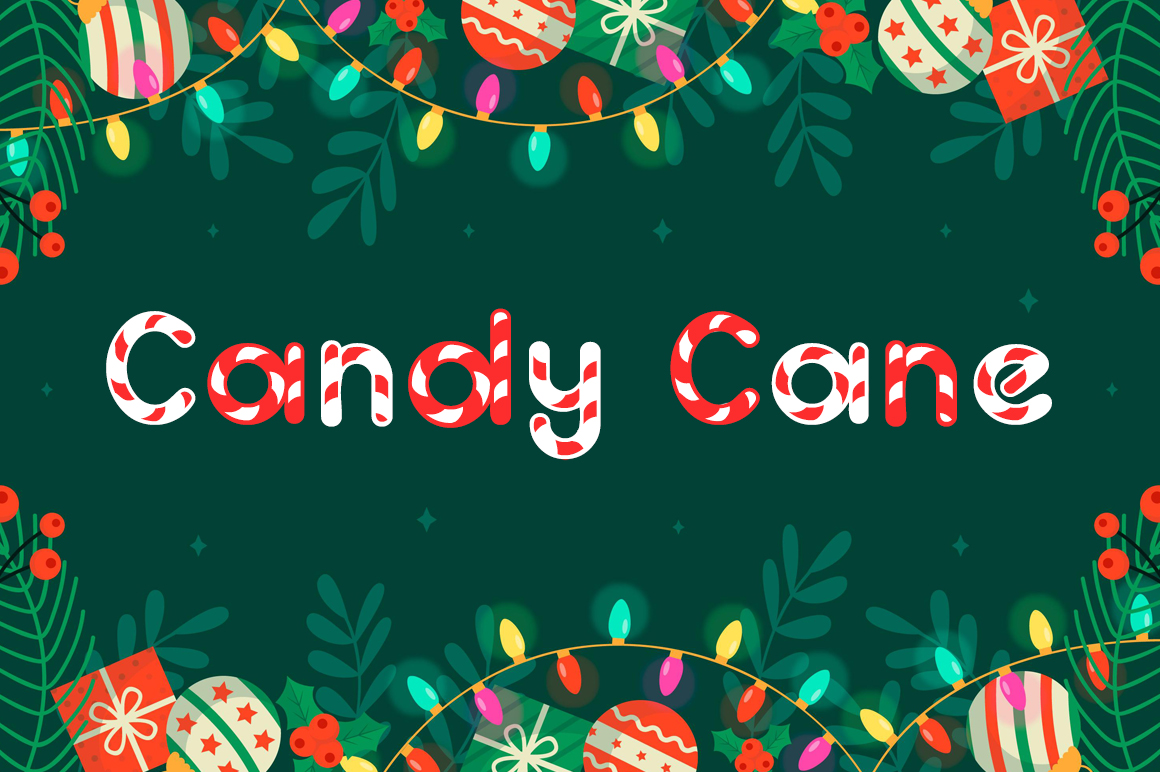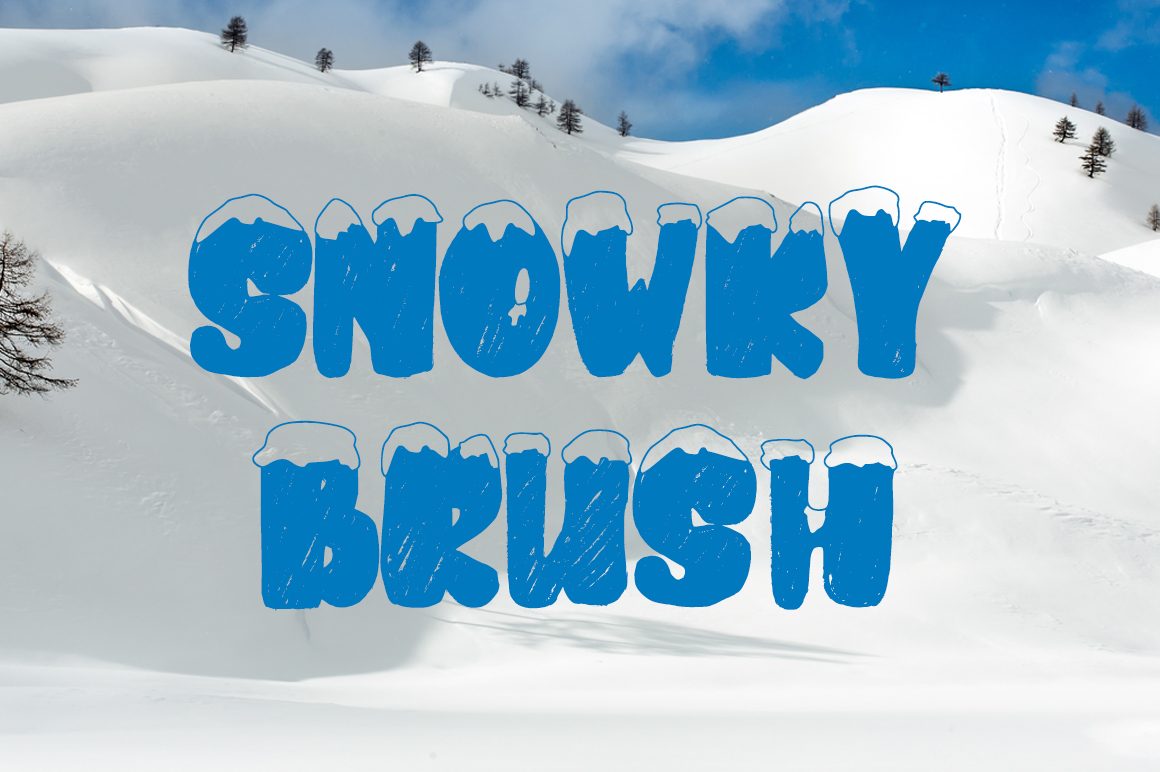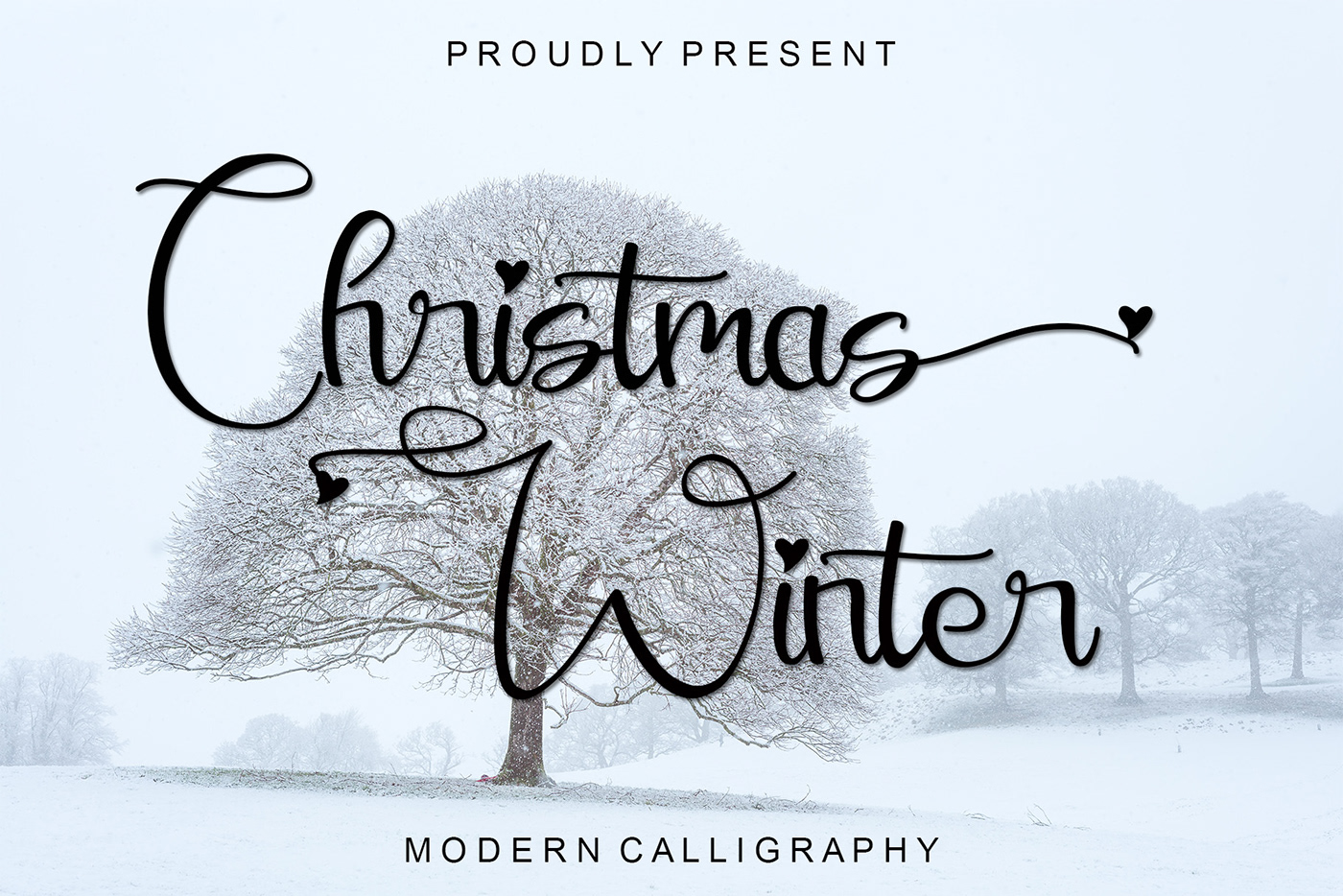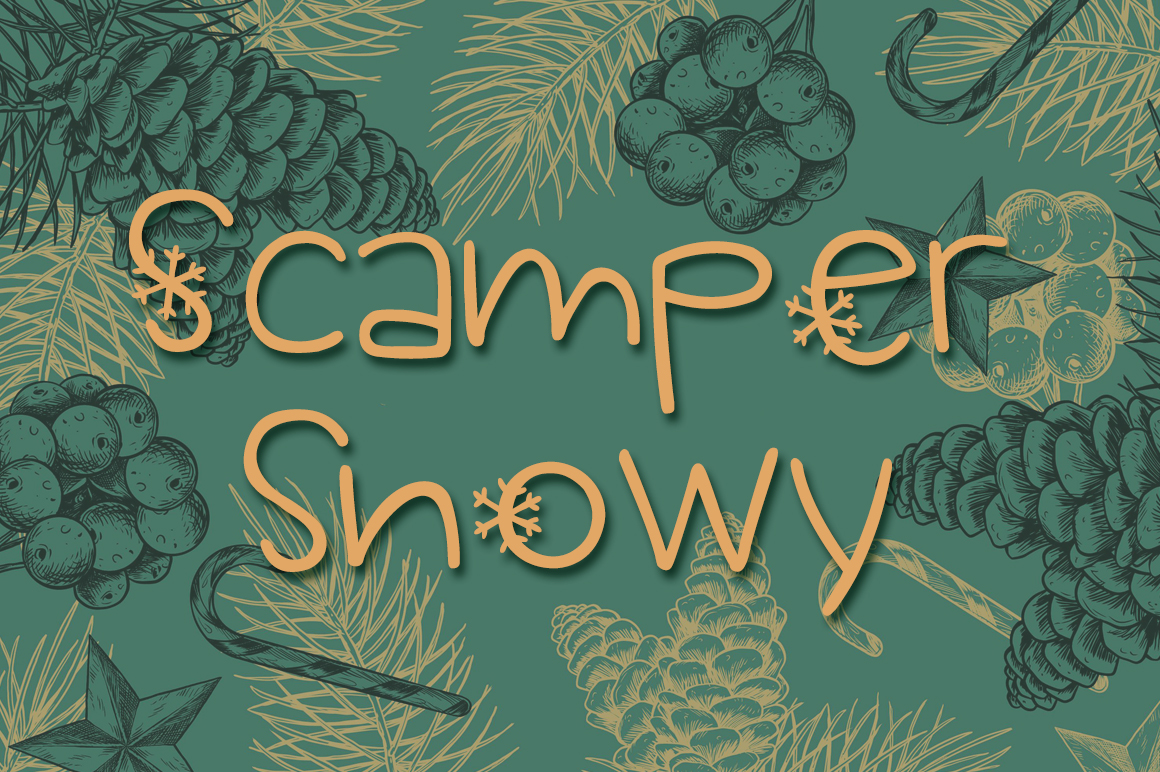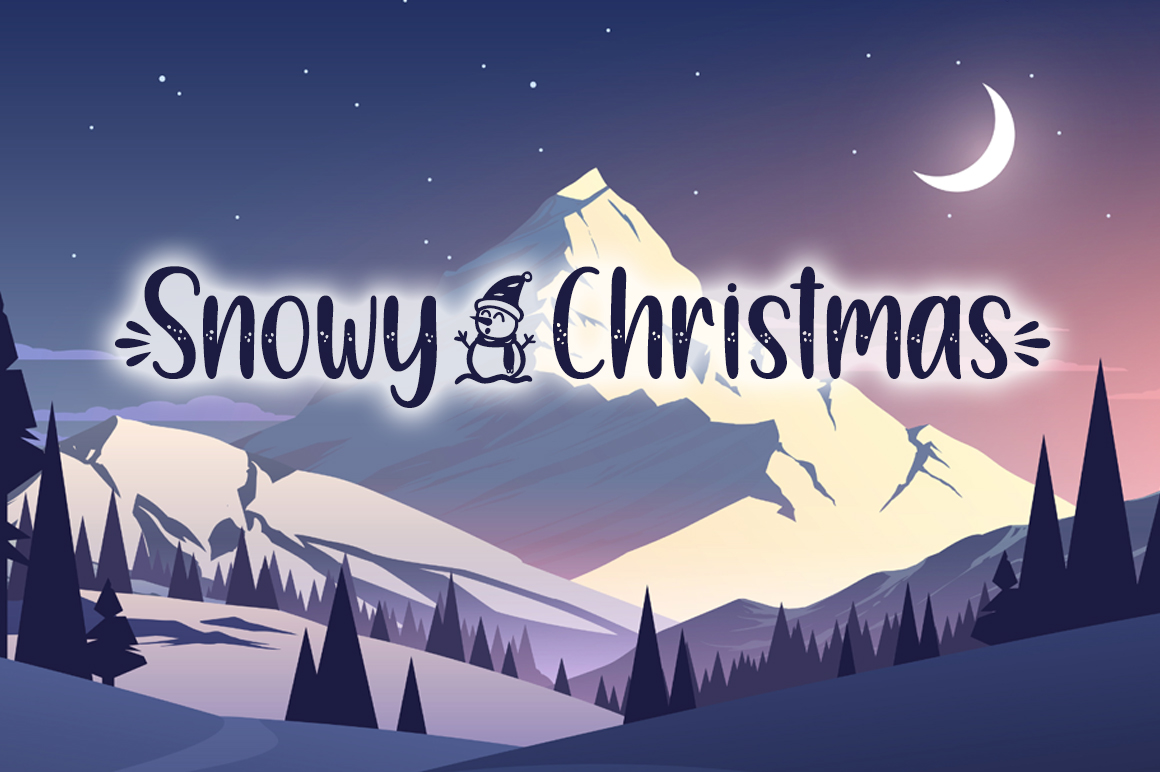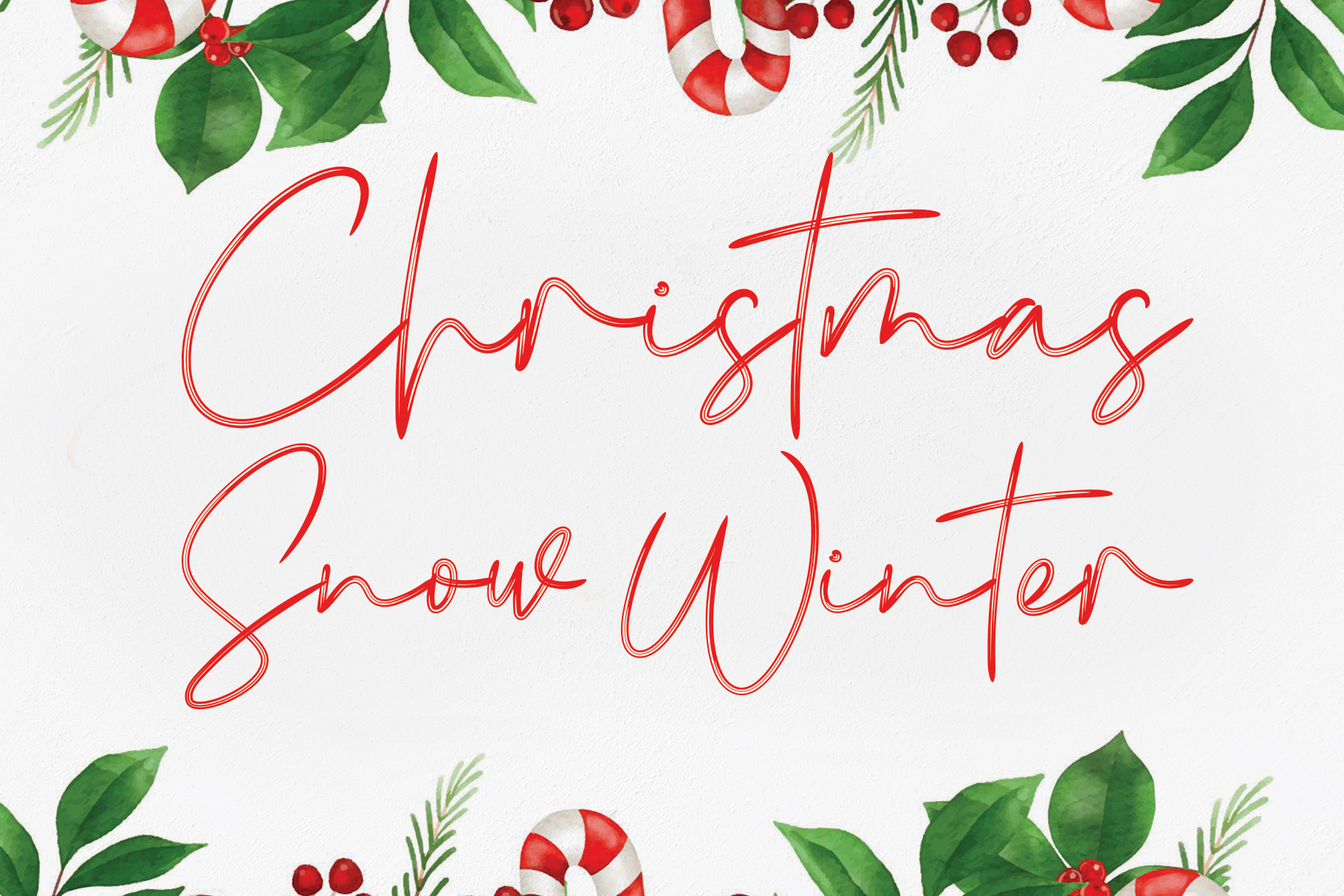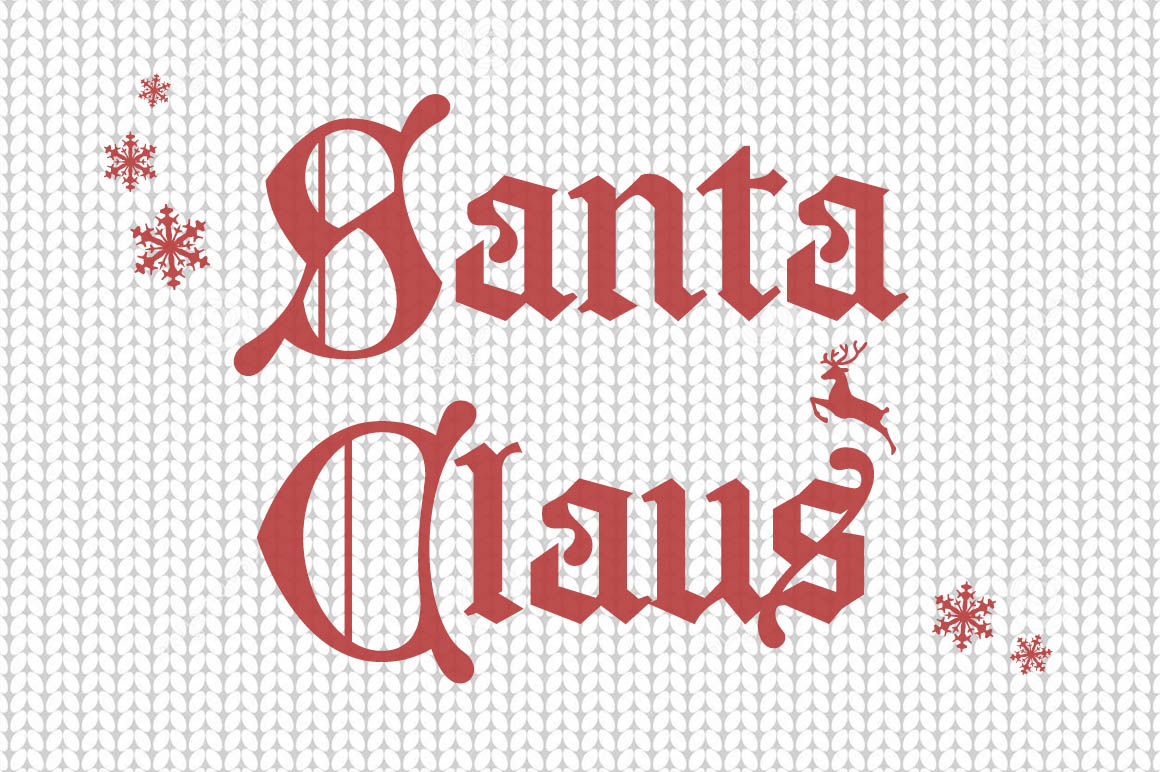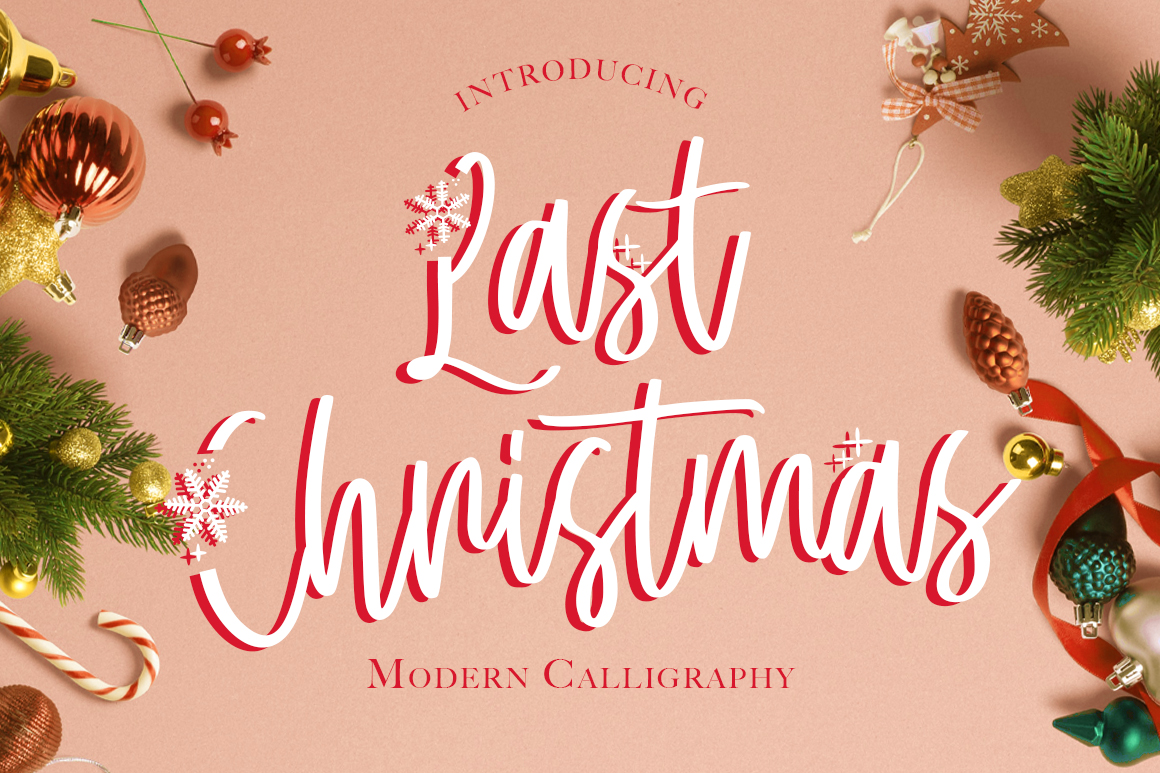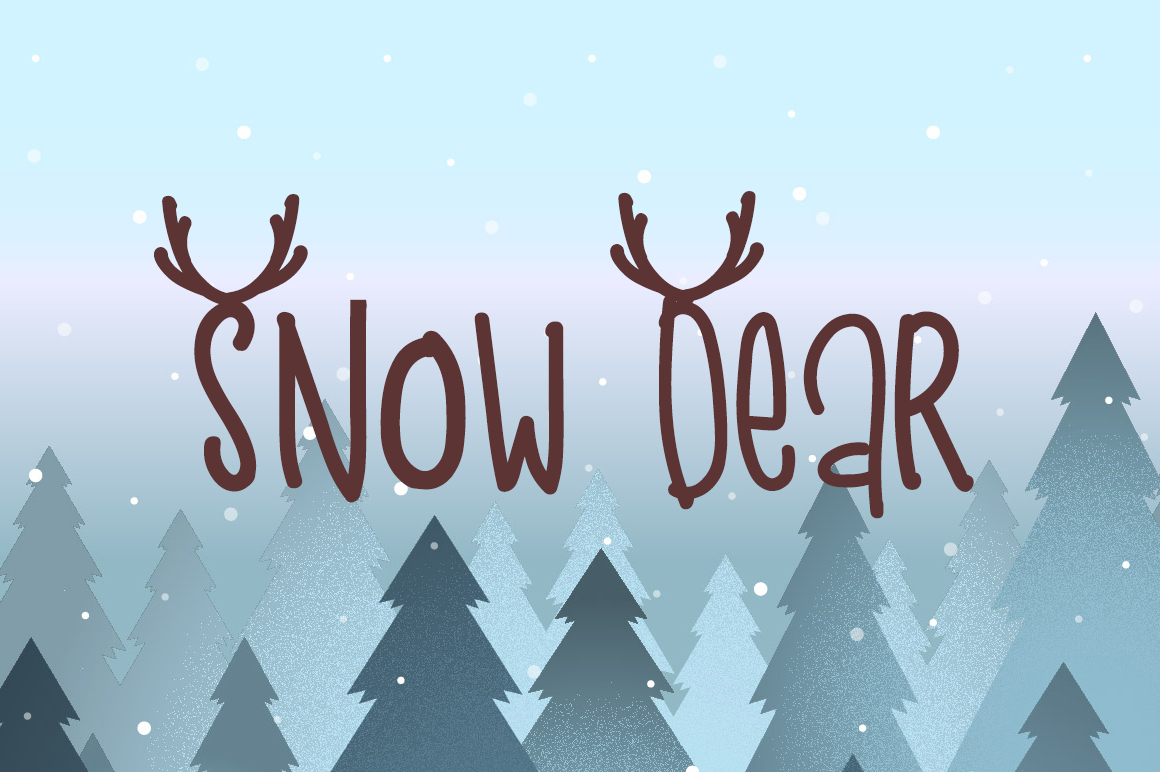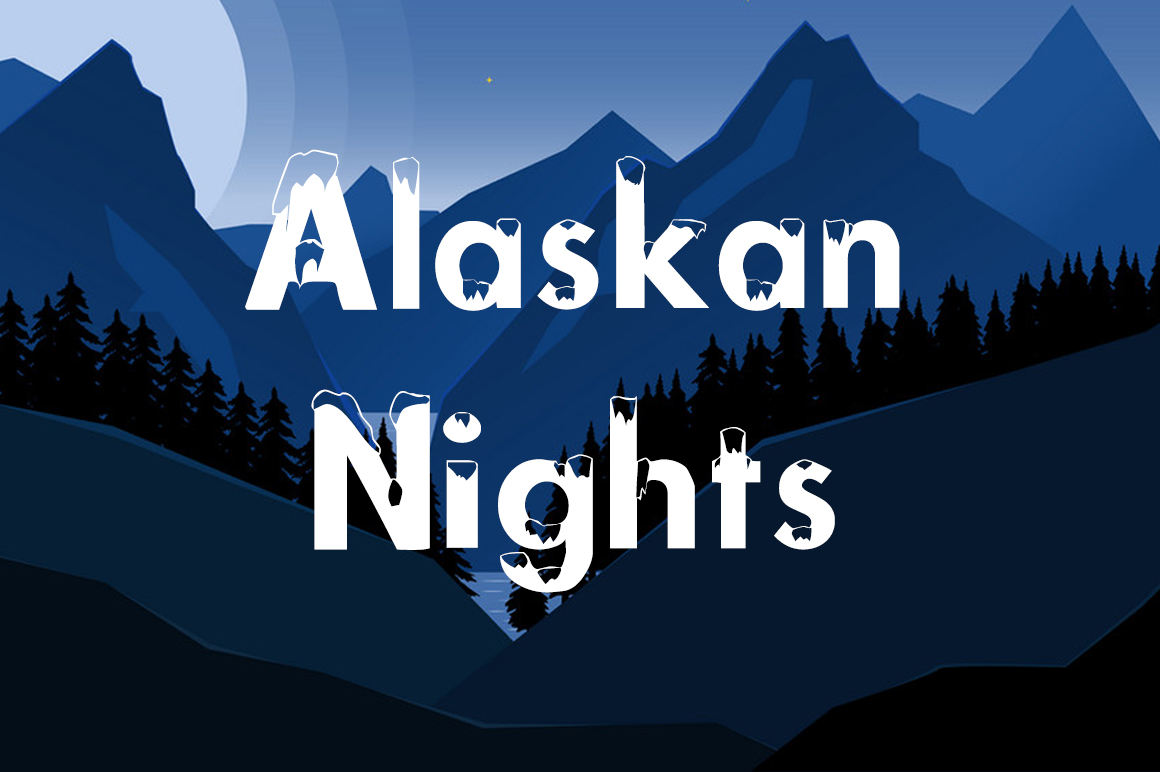
15 typographies gratuites inspirées par l’hiver, la neige et Noël
En ce mois de décembre et à l’approche des fête de fin d’année, vous aurez peut-être des designs avec de la neige, des sapins de Noël ou encore des cadeaux sur lesquels travailler. Par exemple, des affiches, des dépliants, des bannières pour les réseaux sociaux ou des cartes d’invitation que vous allez devoir concevoir avec un thème très hivernal.
Par ailleurs, vous avez certainement entendu à quel point il est important de choisir les polices appropriées pour ces créations visuelles… Aussi, j’ai sélectionné pour vous, quinze polices d’écriture gratuites et merveilleusement  pour tous vos designs !
Certaines de ces typographies intégrons la référence hivernale directement dans les lettrages alors que d’autres seront beaucoup plus subtiles. Dans tous les cas, ce sont des polices que vous pouvez utiliser pour toutes vos créations de Noël et designs de fin d’année.
Christmas Time
Cette typographie dans un style Noël moderne de Lukasz KuIakowski sera idéale pour les titres de vos créations graphiques en cette fin d’année 2020.
Let’s Ski
Let’s Ski est une police d’écriture comportant seulement des lettres majuscules, des chiffres et une ponctuation de base avec un effet neige. Une typographie au style doux et singulier a utiliser pour l’hiver !
Seventeen Winter
Seventeen Winter est un assemblage de deux typographies pour créer une ambiance enneigée dans toutes vos créations graphiques cet hiver.
Santa Claus
Santa Claus est une police d’écriture parfaite pour une gamme de designs graphiques dans un style très traditionnel. Essayez cette typo gratuite pour vous retrouver immédiatement dans un ambiance « Petit Papa Noël » version Tino Rossi !
Last Christmas
Last Christmas est une police manuscrite conviviale et fraîche. Elle sera idéale pour vos cartes de vœux ou pour tout projet graphique nécessitant une touche élégante.
Snow Dear
Chaque lettre majuscule de cette typographie gratuite est ornées de bois de renne pour être parfaitement dans l’esprit de Noël.
Christmas Surprise
Utilisez la typographie gratuite Christmas Surprise pour apporter le joie et l’esprit de Noël sur vos supports graphiques de fin d’année !
Alaskan Nights
La police d’écriture gratuite Alaskan Nights est idéal pour apporter un petit coup de froid à vos créations graphiques.
Merry Christmas
Cette police d’écriture manuscrite et complètement vintage donnera à vos supports graphiques un esprit de Noël indiscutable.
Candy Cane
Si vous aimez ces bonbons rouges et blancs en forme de canne accrochés aux branches du sapin de Noël et qu’ils vous rappellent de bons souvenirs alors n’hésitez pas à utiliser cette typographie gratuite.
Snowky Brush
La typographie fantaisiste Snowky Brush vous transportera directement sur une piste enneigée avec snowboard attaché aux pieds. Elle sera parfaite pour apporter un côté cool à vos supports de communication cet hiver.
Scamper Snowy
Cette police d’écritiure gratuite apportera une touche de fantaisie hivernale à vos créations graphiques tout en restant très professionnelle.
Christmas Winter
La typographie élégante Christmas Winter créee par Ahmad Afandi est gratuite pour un usage personnel et comporte des lettres majuscules et minuscules.
Snowy Christmas Font
La typographie fantaisiste Gingerbread House créee par Chris Hansen est gratuite pour un usage personnel et comporte des lettres majuscules et minuscules!
Christmas Snow Winter
La typographie fantaisiste Gingerbread House créee par Chris Hansen est gratuite pour un usage personnel et comporte des lettres majuscules et minuscules.